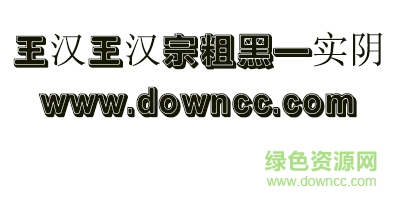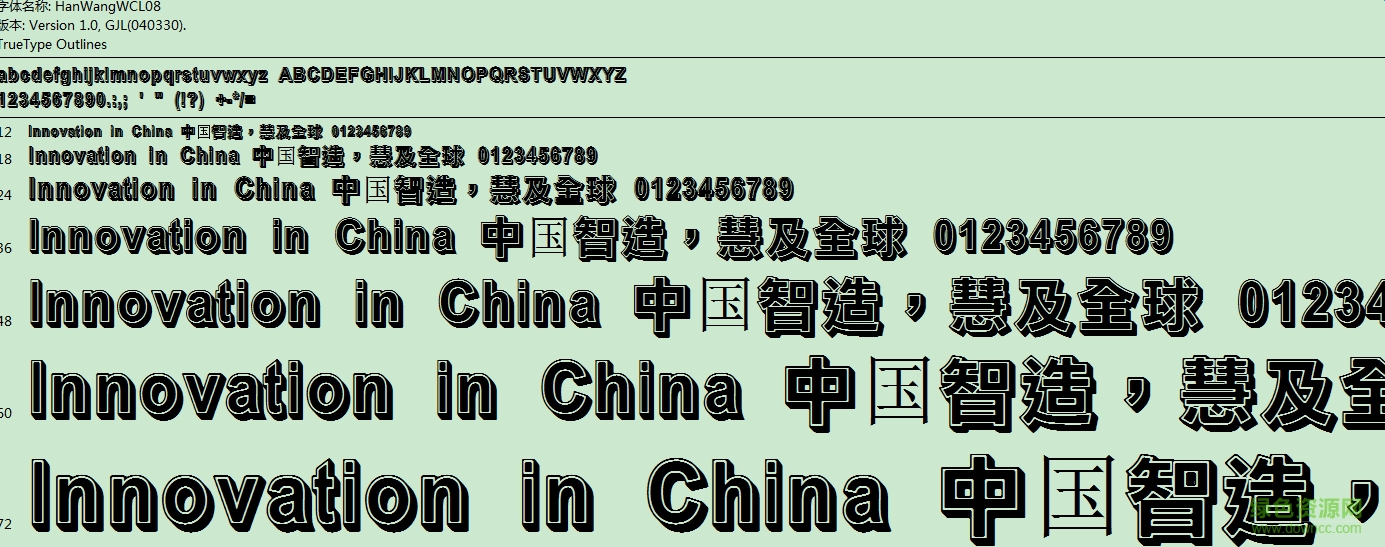
王漢宗粗黑體-實陰是一個很實用的黑體字體文件。小編為大家?guī)淼倪@款字體文件不僅可以用于平面設(shè)計,還可以用于報考排版使用。字體美觀不呆板!喜歡的用戶歡迎下載。
王漢宗粗黑體—實陰字體用途廣泛,適用于海報、廣告設(shè)計等方面,小編為大家提供免費下載地址。快來綠色資源網(wǎng)踴躍下載吧!